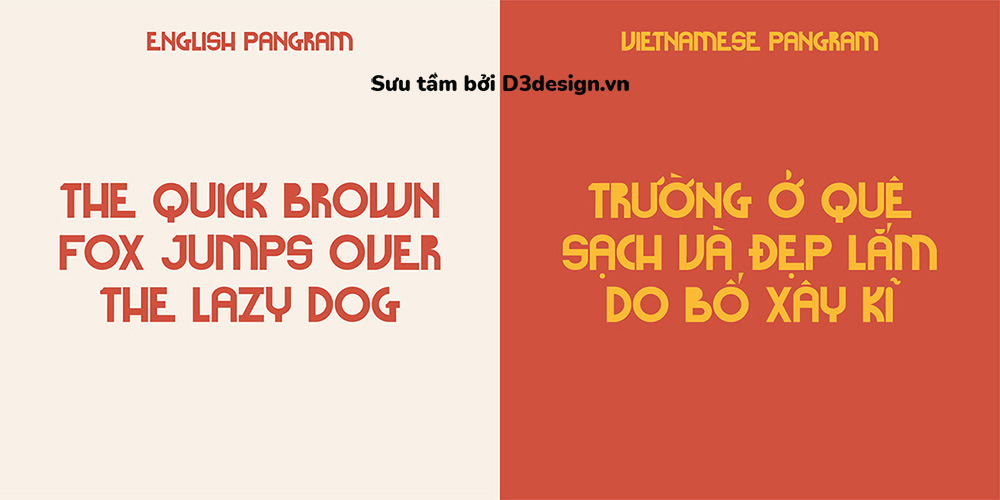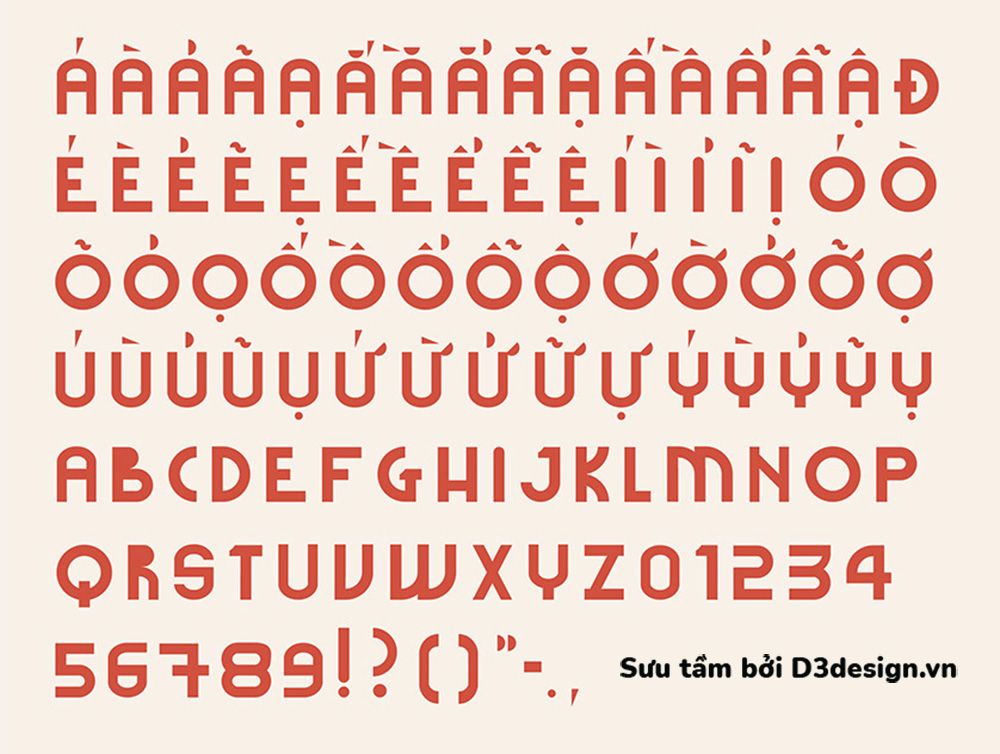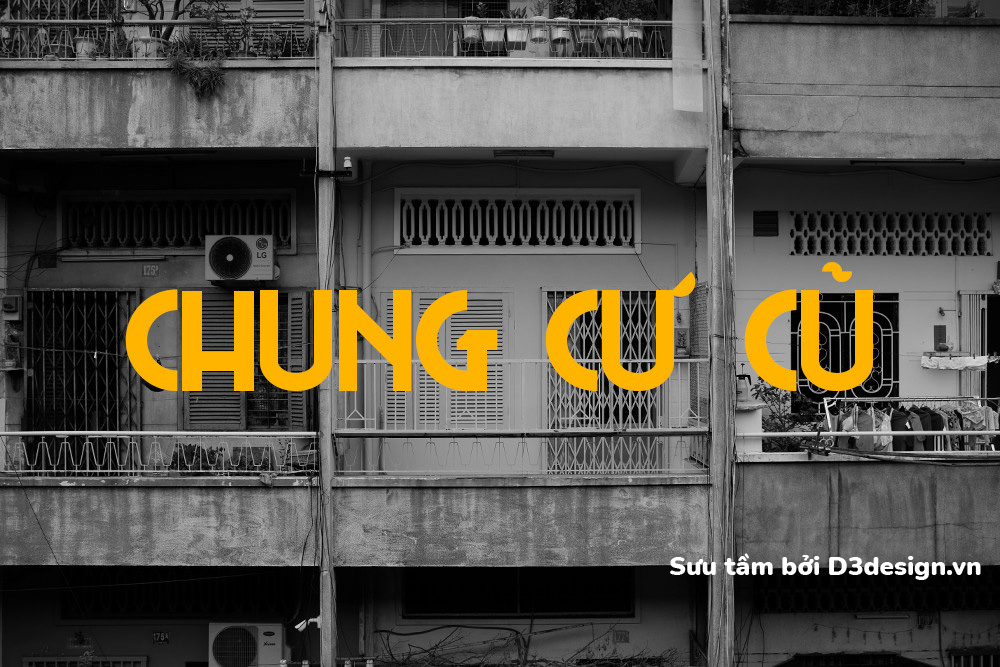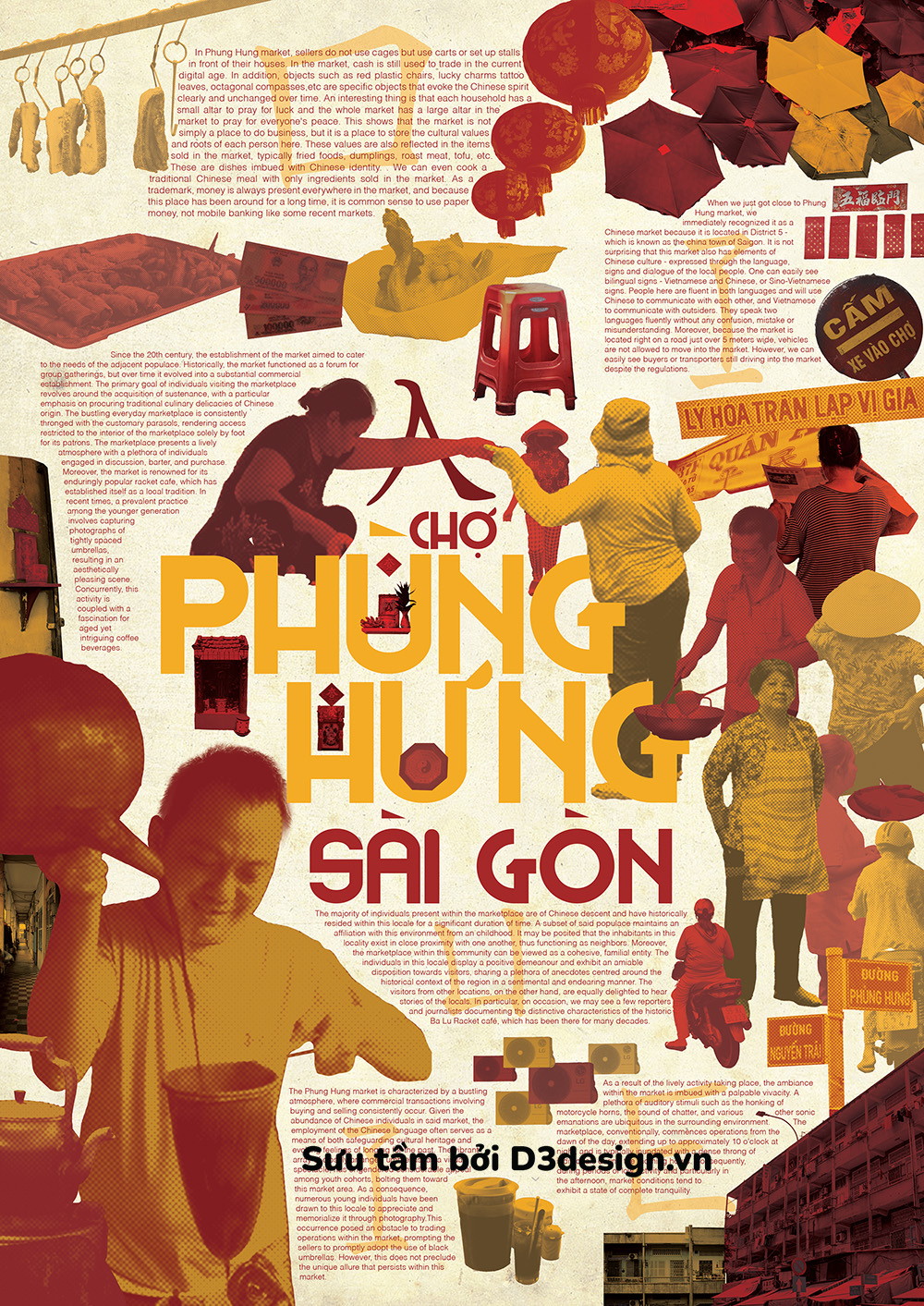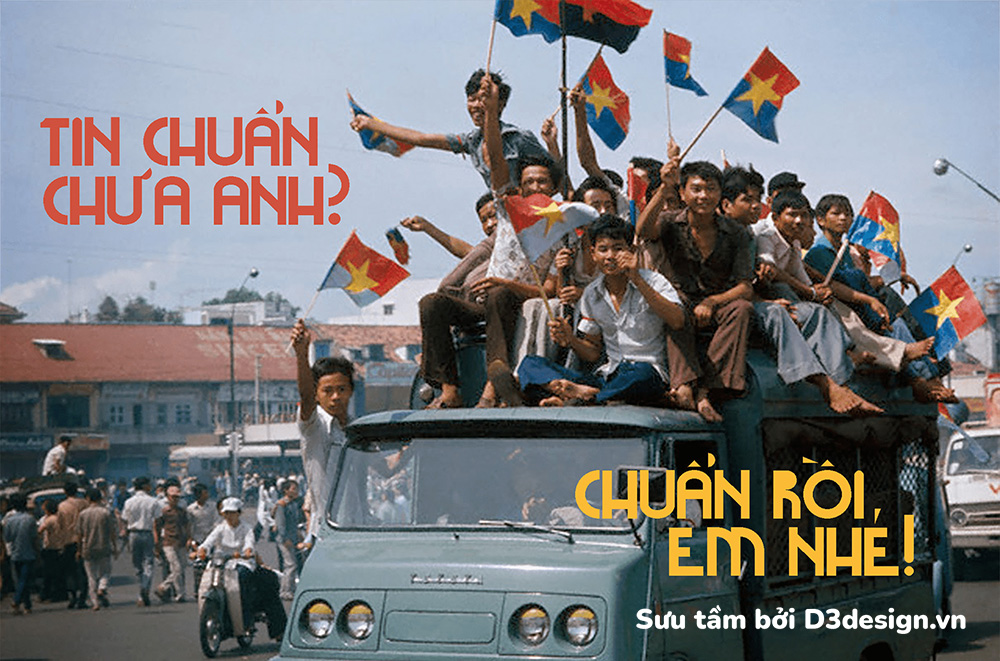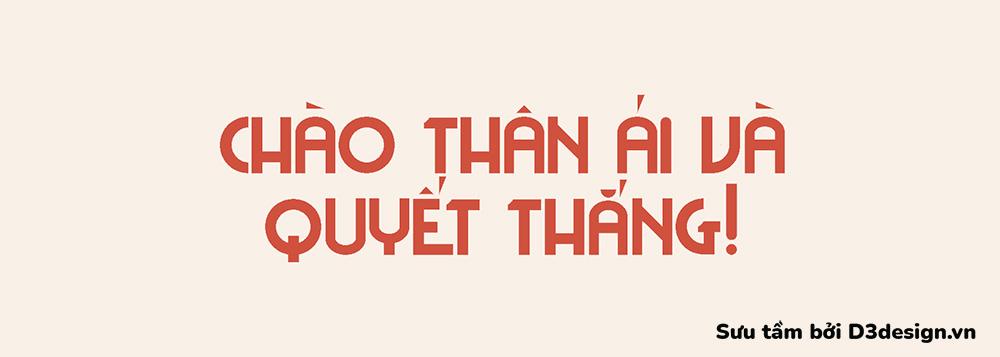
Font Việt Hóa - Doc Lap Typeface Mang Phong Cách Đậm Chất Áp Phích Việt Nam Xưa
Độc Lập (Independence) là một kiểu chữ dựa trên phong cách phông chữ đậm của áp phích Việt Nam trong thời chiến. Nó lấy cảm hứng từ Nghệ thuật Tuyên truyền - một thứ 'vũ khí' hữu hiệu trong kháng chiến chống đế quốc. Như vậy, kiểu chữ nhằm khơi dậy lòng yêu nước và niềm vui thống nhất đất nước khi nhìn lại lịch sử dựng nước của Việt Nam.